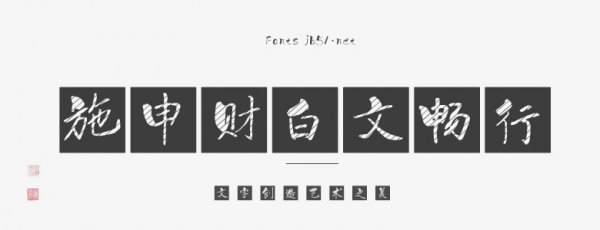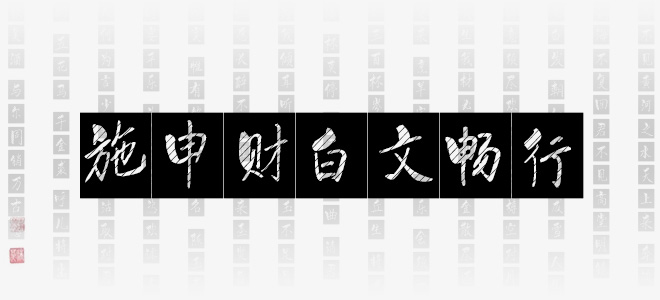
施申財(cái)白文暢行是一款非常個(gè)性的書(shū)法藝術(shù)字體,字形端正,具有很好的視覺(jué)感,適合于文化類的宣傳設(shè)計(jì)、商業(yè)類品牌的廣告和產(chǎn)品包裝設(shè)計(jì)以及個(gè)性化文字排版等較多場(chǎng)景。
施申財(cái)白文暢行